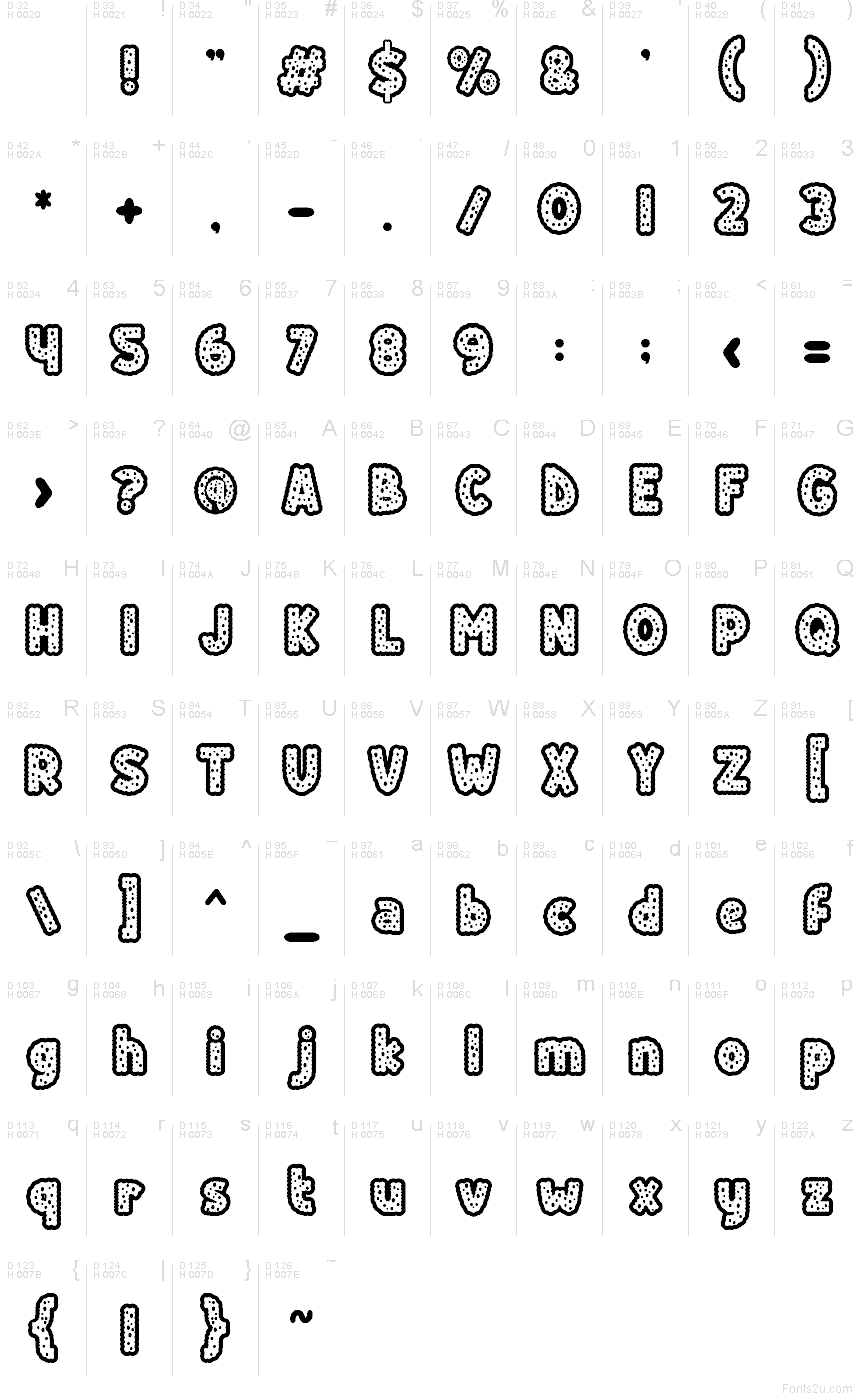
Cake Couture Two
Cake Couture Two von Putracetol Studio ist eine kostenlose Display-Schriftart für den Bäckereibereich, deren weiche, aufgeplusterte Buchstaben aussehen, als wären sie mit Zuckerguss gespritzt und mit Streuseln verziert. Die abgerundeten Formen, die dicken, dunklen Konturen und die gepunktete Füllung verleihen dem Alphabet einen charmanten Comic-Charakter, der eher an verzierte Kekse erinnert als an gewöhnliche Schriftzeichen.
Diese kostenlose Schriftart eignet sich perfekt für Süßwarenverpackungen, Café-Speisekarten, Partyeinladungen, Bäckerei-Logos und fröhliche Social-Media-Posts, bei denen der Name schon auf den ersten Blick appetitlich wirken soll. Sie ist zudem ideal für kurze Überschriften, stickerartige Etiketten und Kindertitel, da die kräftigen Buchstaben das süße Thema wunderbar in den Mittelpunkt rücken.